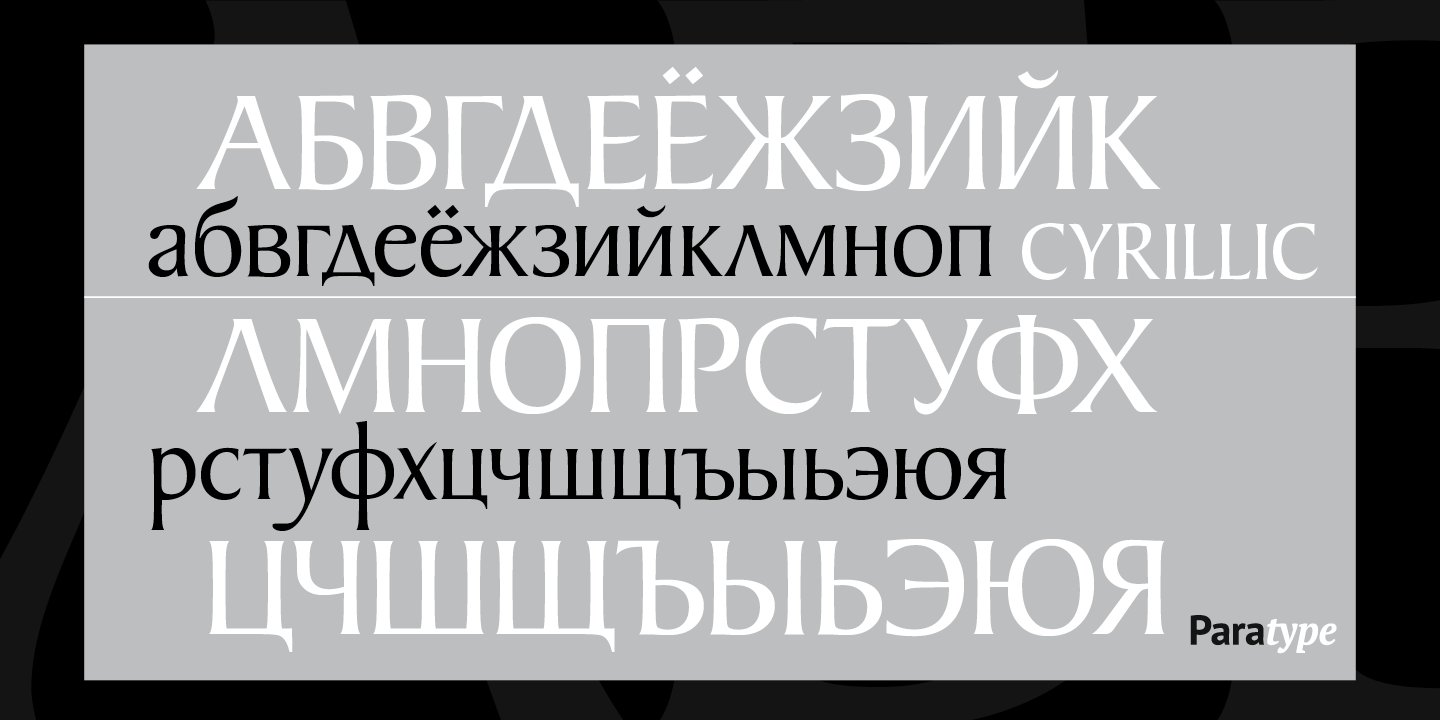
Die Baker Signet des US-amerikanischen Kalligrafen Arthur Baker erschien in den 1960er-Jahren als Fotosatzschrift. Vom Normalschnitt existieren zahlreichen Digitalisierungen (Linotype, Bitstream, Paratype [einschl. kyrillisch], Tilde und Arthur Baker selbst). Eine besonders umfangreiche Digitalisierung in 14 Schnitten gibt es als Sigvar Serial von SoftMaker.
Fotosatzversion
Kyrillische Version von ParaType